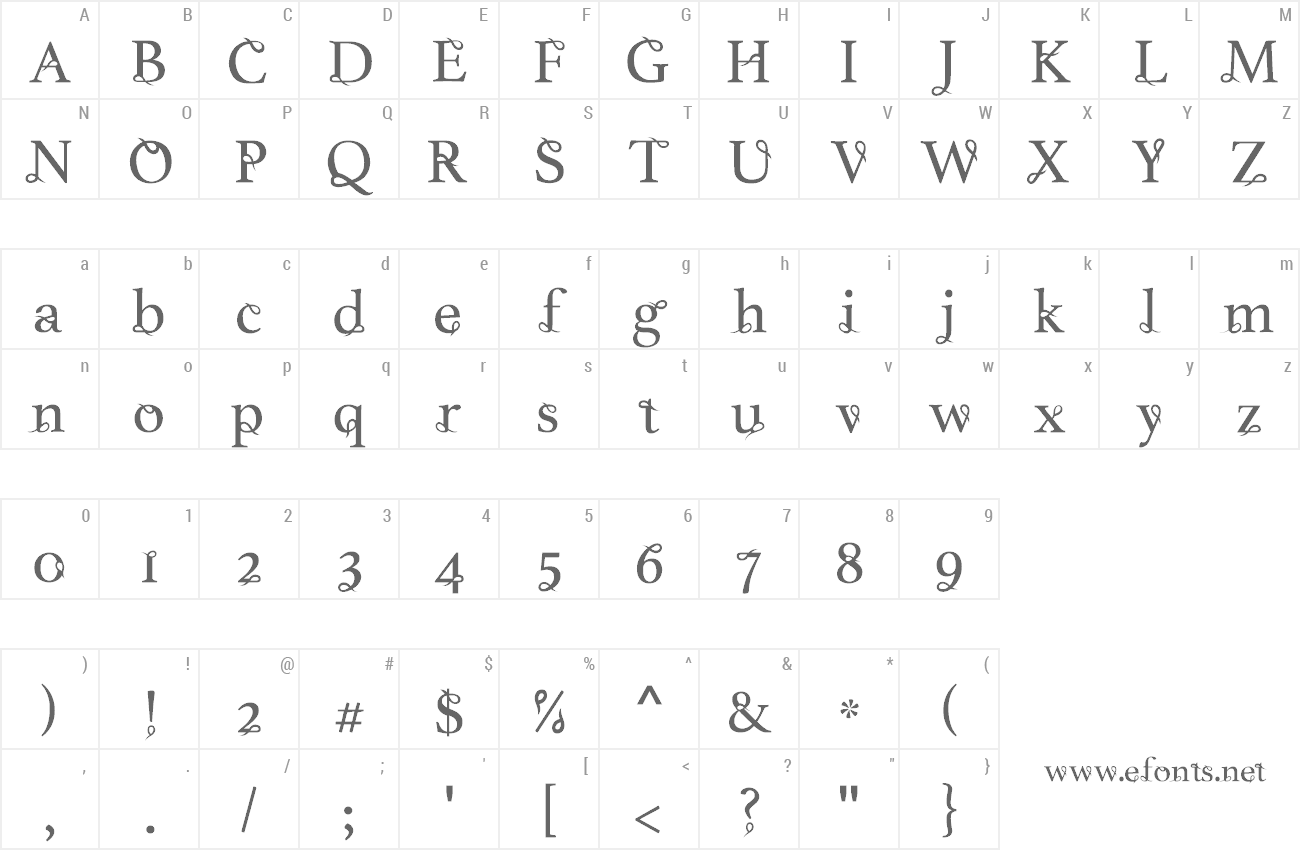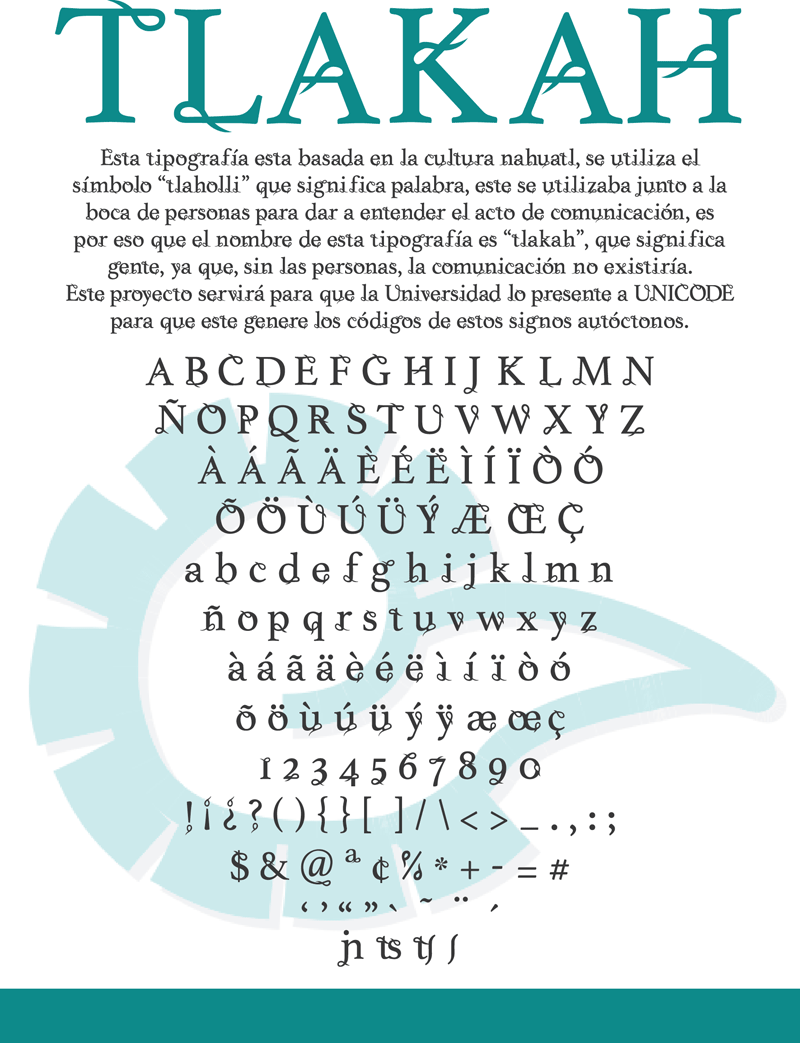
Preview and download Tlakah Font. Created by Galia Atri in Basic Various styles with 100% Free license.
| Font name: | Tlakah |
| Author: | Galia Atri |
| Esta tipografía esta inspirada en la cultura nahuatl, por lo que el nombre tlakah significa gente en la lengua de esta cultura, así mismo cuenta con signos especiales de la cultura que se siguen utilizando hoy en día. |